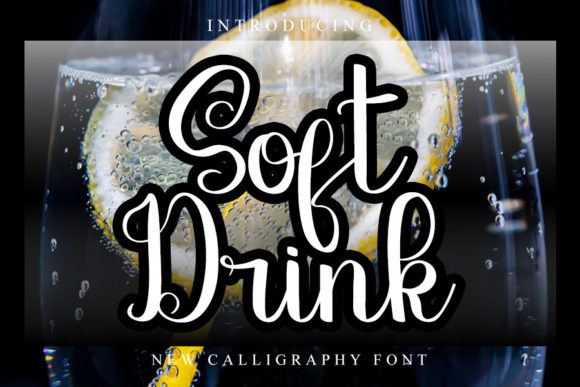
Soft Drink
Découvrez Soft Drink – La Police Manuscrite Élégantes et Moderne
Si vous recherchez une police manuscrite qui allie classe, fluidité et une touche de tradition calligraphique, alors **Soft Drink** est la solution idéale pour vos projets de design. Conçue pour les graphistes, les concepteurs de marques et les typographes passionnés, cette fonte offre un équilibre parfait entre style et lisibilité, transformant n'importe quel texte en une œuvre d'art élégante.
- Style Manuel et Raffiné – Chaque trait est soigneusement dessiné à la main, évoquant l'art intemporel de la calligraphie classique tout en restant pleinement adaptée à la création graphique contemporaine.
- Formes Équilibrées et Variées – Des majuscules fluides aux minuscules organiques, Soft Drink offre une grande variété de formes qui s'adaptent à toutes les tailles de projet, des logos aux mises en page de livres.
- Amélioration de l'Esthétique des Projets – Cette police est conçue pour rehausser visuellement n'importe quelle conception, ajoutant une touche sophistiquée qui capte l'attention et communique élégance.
Que vous soyez en train de créer une identité de marque, une couverture de livre, ou une affiche tendance, Soft Drink apporte une authenticité et une chaleur qui Captivent votre public. Son style handwritten moderne et sa qualité impeccable en font un choix incontournable pour tout designer souhaitant une police manuscrite de haute qualité sans compromis sur la fonctionnalité.